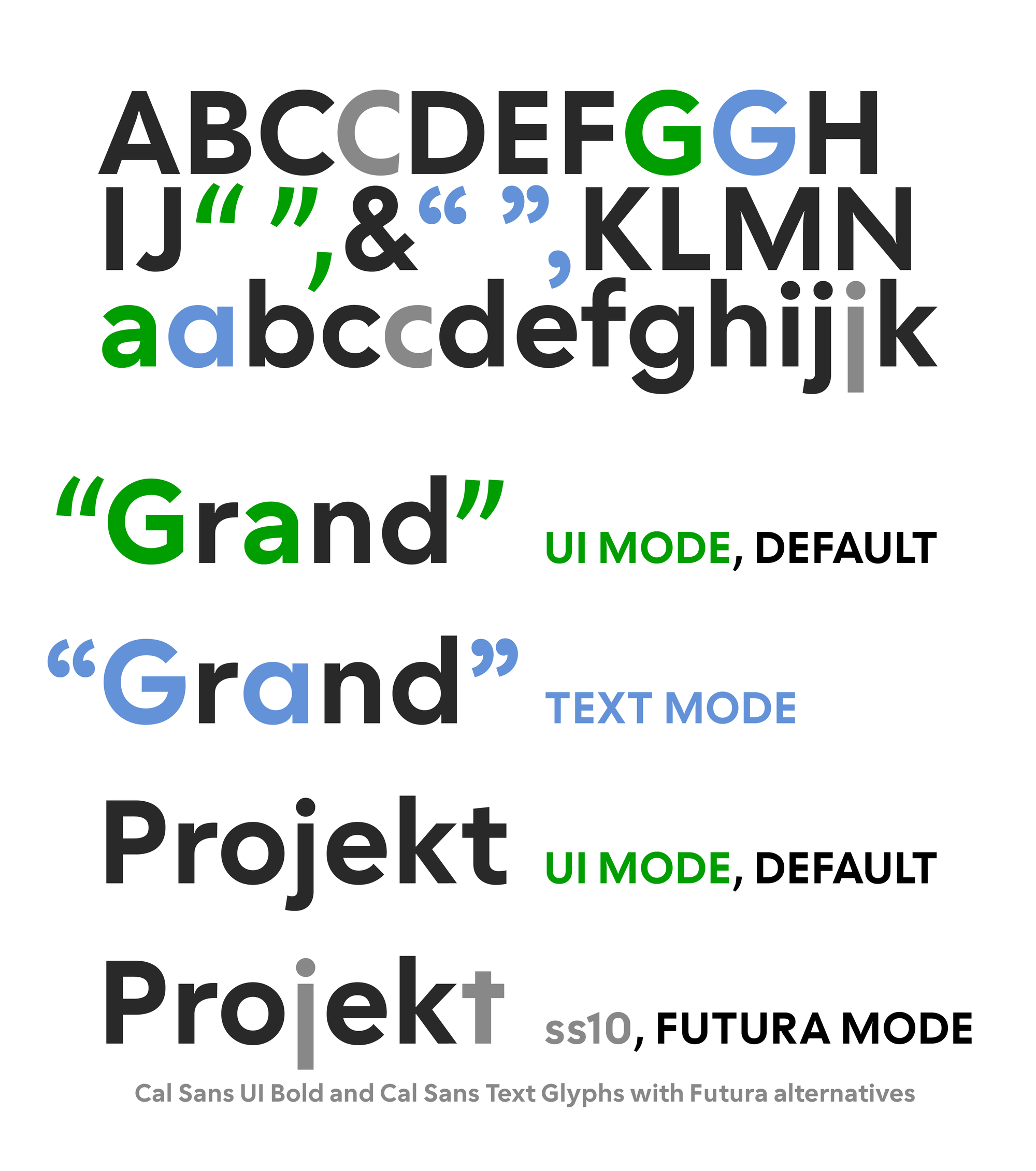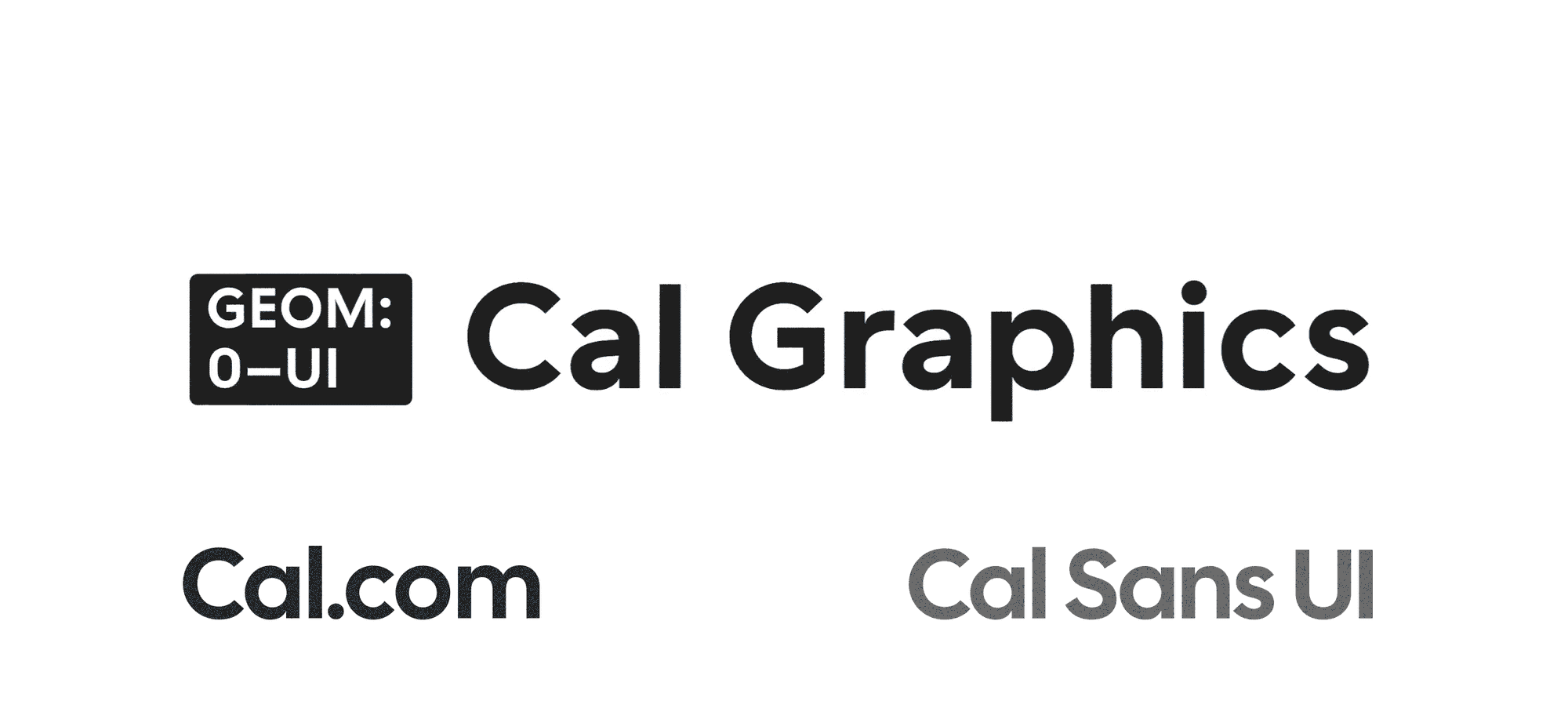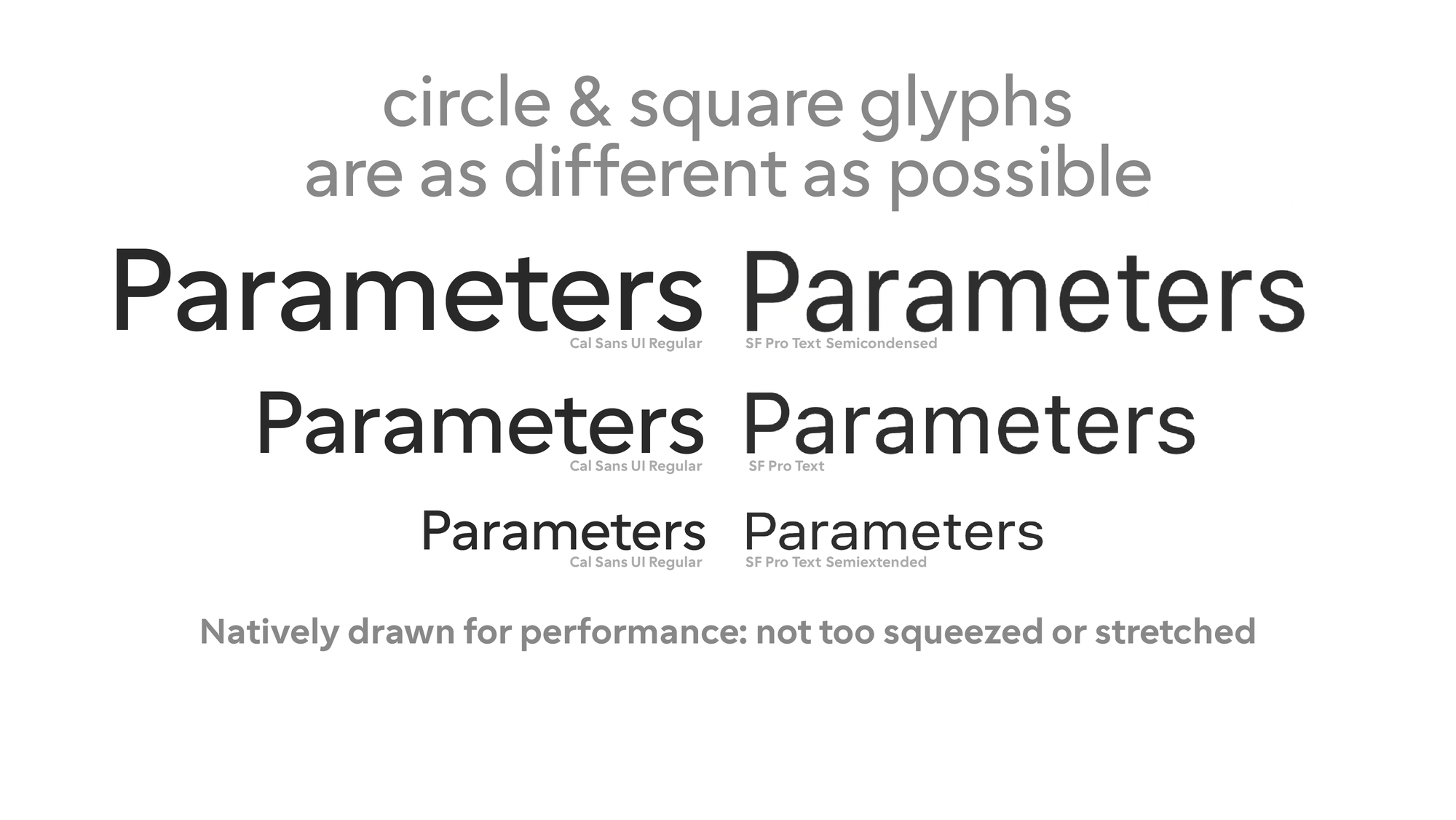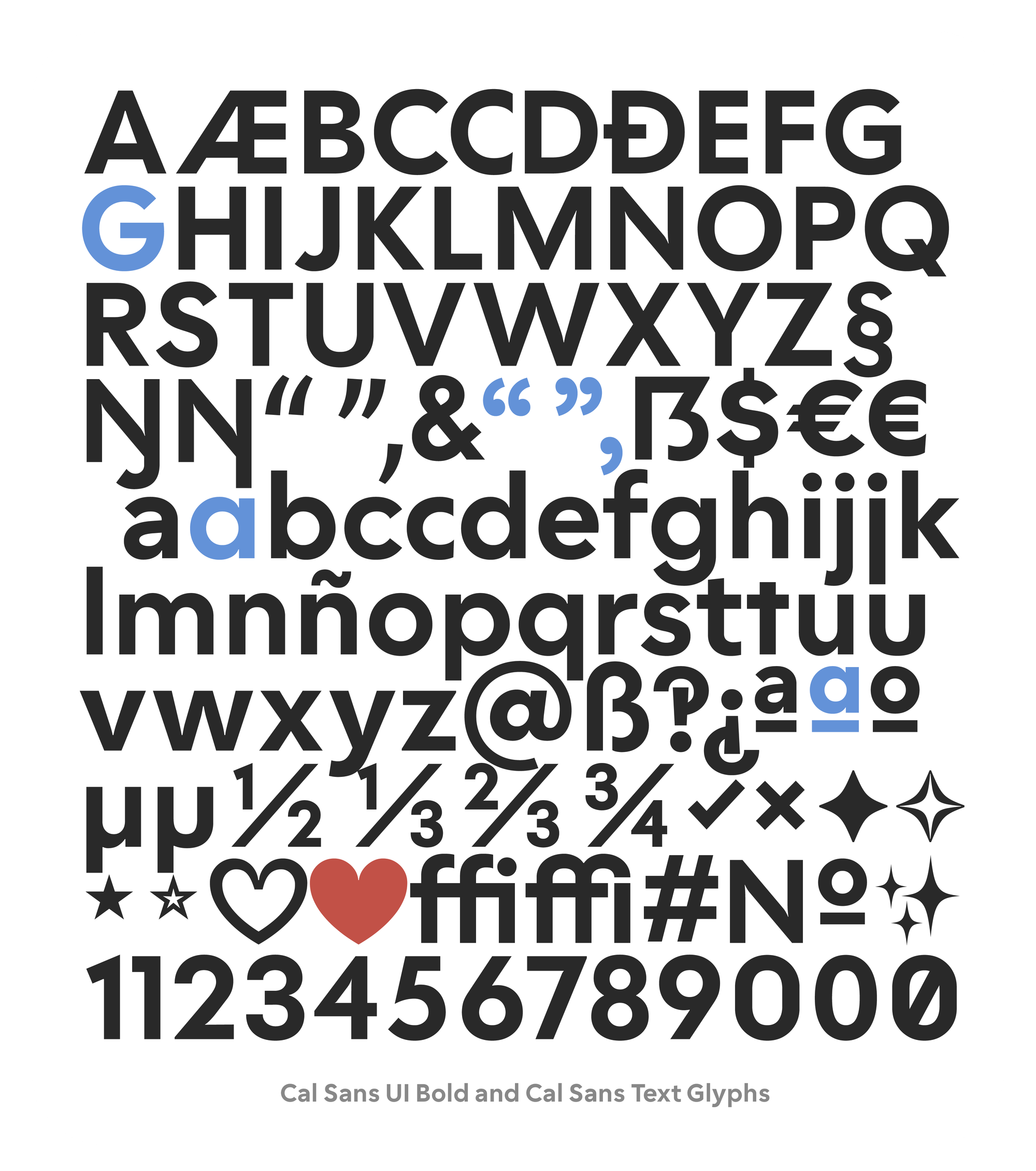
Cal Sans UI là một typeface biến thể (variable typeface) được tạo ra bởi Mark Davis cho Cal.com, sở hữu một trục GEOM cho phép chuyển đổi mượt mà giữa các hình thái humanist và geometric. Nó được phát hành dưới giấy phép SIL Open Font License, miễn phí cho cả mục đích cá nhân và thương mại.
Cal.com, nền tảng lập lịch mã nguồn mở với hơn 50.000 sao trên GitHub, đã ủy thác dòng typeface này từ WORDMARK, từ thực hành kiểu chữ của Davis. Kết quả không phải là một font UI chung chung. Cal Sans UI bao gồm ba dòng font riêng biệt: Cal Sans UI, Cal Sans UI Text, và Cal Sans UI Geo, mỗi dòng đều có trục trọng lượng (weight axis) trải dài từ Light đến Bold và trục GEOM tùy chỉnh chạy từ 0 đến 100. Ở mức GEOM 0, các ký tự mang đường cong hữu cơ, nhân văn. Ở mức 100, chúng trở thành các tỷ lệ hình học nghiêm ngặt. Font này chuyển đổi liên tục giữa cả hai trạng thái, mang lại cho các nhà thiết kế một công cụ với phạm vi biểu cảm thực sự.
Dòng font này được xây dựng dành riêng cho giao diện, được tối ưu hóa cho việc hiển thị ở độ phân giải 14–15px trên các màn hình mật độ cao. Các chỉ số dọc (vertical metrics) được căn chỉnh theo các tiêu chuẩn UI như Inter, Geist, Roboto và các chuẩn hệ thống khác, vì vậy việc đưa font Cal Sans UI miễn phí vào bất kỳ codebase hiện có nào sẽ không đòi hỏi bất kỳ điều chỉnh bố cục nào. Năm mức trọng lượng được hỗ trợ trên cả ba dòng font, và typeface này xử lý được hơn 100 ngôn ngữ.